La tipografía es uno de los elementos más importantes del diseño gráfico, ya que influye en la legibilidad, la estética, el estilo y el mensaje de cualquier proyecto.
Elegir la fuente adecuada para tu diseño cristiano puede marcar la diferencia entre el éxito y el fracaso, entre captar la atención y el interés de tu congregación, o pasar desapercibido y aburrido. Por eso, es fundamental estar al día de las tendencias tipográficas, y conocer las fuentes más populares y demandadas por los diseñadores en cada momento.
En este artículo, te vamos a mostrar las fuentes más populares para los diseñadores en 2024, y cómo puedes aplicarlas para crear diseños cristianos impactantes, originales y profesionales.
#1 Gellisto
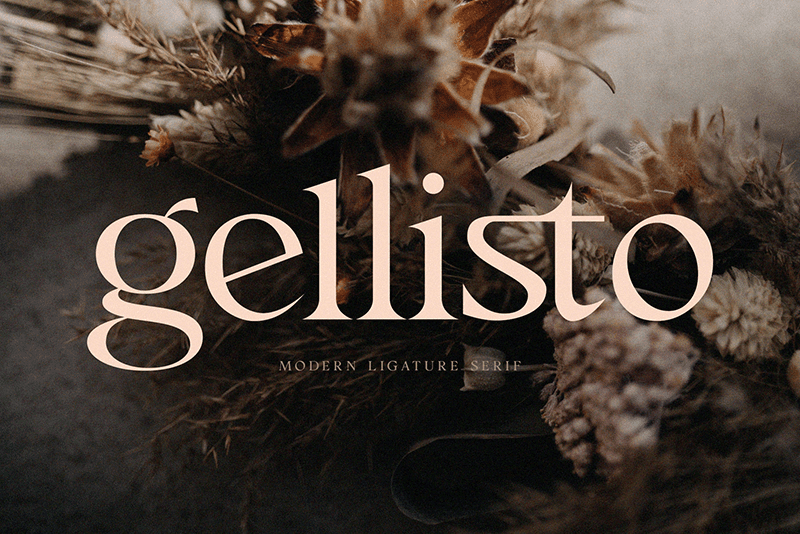
Presentamos Gellisto Modern Ligature Serif. Gellisto es una tipografía serif moderna, elegante y sofisticada, ideal para usar como display para encabezados, logotipos, branding, revistas, empaques de productos e invitaciones. Gellisto tiene líneas limpias y curvas suaves que le dan a cualquier proyecto un toque extra de clase.
#2 Nexa
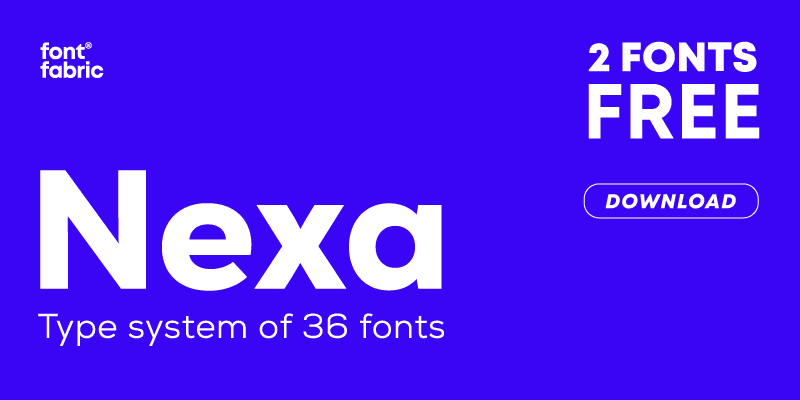
La familia de fuentes Nexa es adecuada para encabezados de todos los tamaños y bloques de texto tanto en el ancho y el alto máximo como mínimo. Los estilos de fuente Nexa son aplicables para cualquier tipo de diseño gráfico digital, web, impreso, superficies duras, telas junto con carteles, logotipos y branding.
#3 Billion Dreams
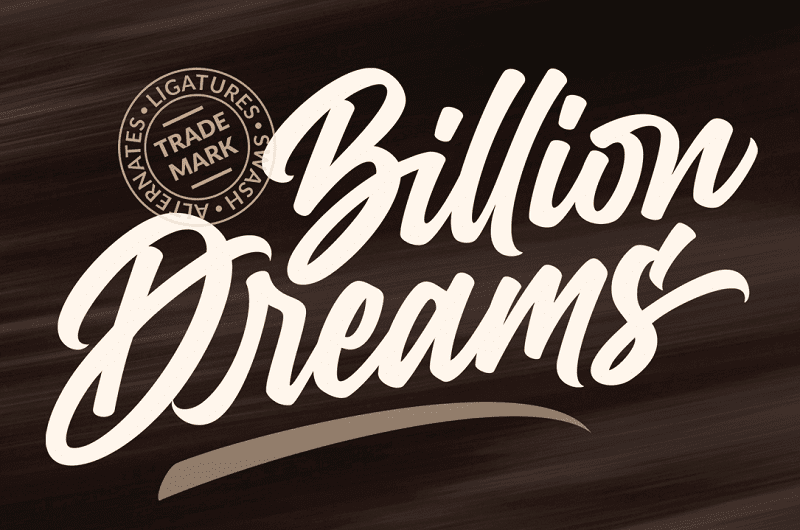
Se trata de una grandiosa fuente script que simula un trazo a mano. Perfecta para refrescar un diseño y hacerlo amigable.
#4 Lostar
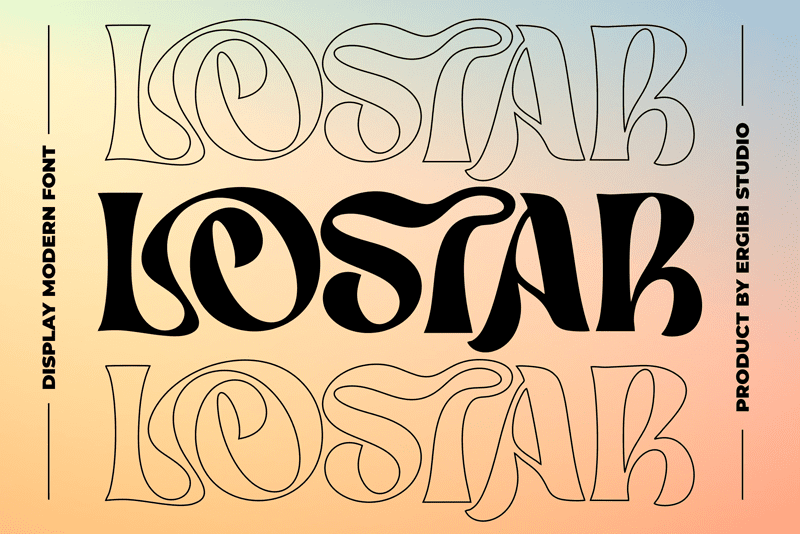
Fuente Moderna de Pantalla. Esta fuente tiene una forma de letra única y audaz, que la hace ideal para ser utilizada en temas de diseño modernos y minimalistas. Las ligaduras únicas en la serif hacen que este tipo de letra sea fresco y se destaque más que la fuente serif regular, perfectamente para titulares, logotipos, carteles, empaques, camisetas, cafeterías, restaurantes, encabezados de revistas, letreros o tarjetas de regalo/postales, cafés y bodas o cualquier tipo de propósito publicitario.
#5 Big Noodle Titling
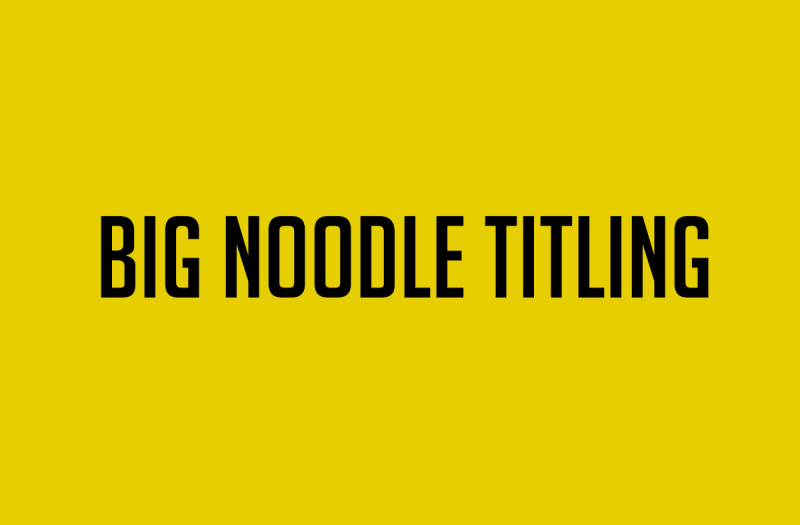
Esta es una fuente sans serif moderna con 3 fuentes! Presentamos Big Noodle Titling. Un conjunto genérico de mayúsculas construido sobre el principio de ancho uniforme gótico, construido a partir de formas cuadradas y un acabado simplificado, Big Noodle Titling ofrece una excelente claridad en cualquier medio. Las características clave de Big Noodle son su utilidad y su aspecto poco notable.
#6 Bebas
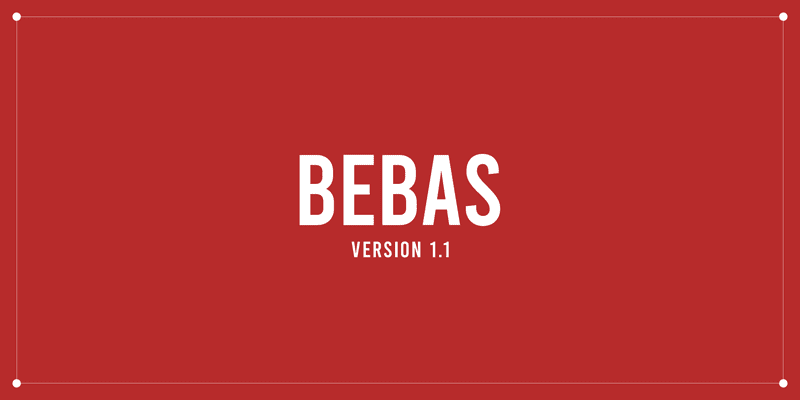
Bebas es una fuente de visualización gratuita para titulares, subtítulos y títulos diseñada por Ryoichi Tsunekawa.
#7 Camera Obscura
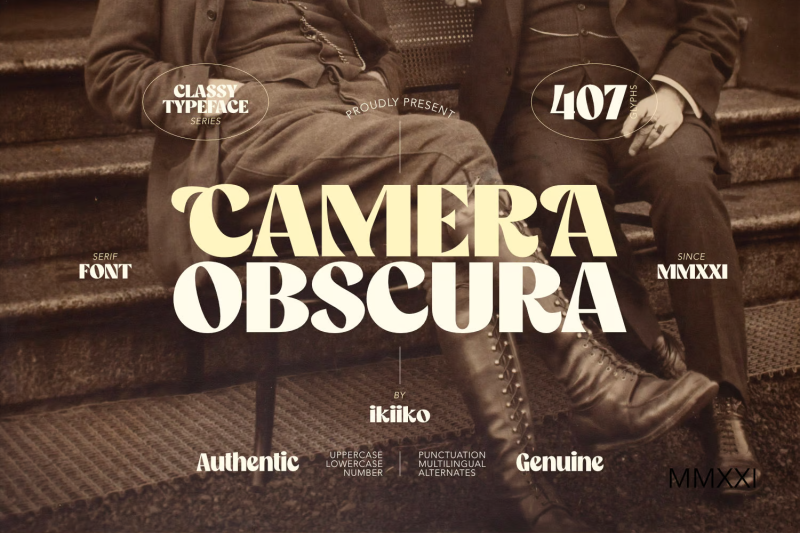
Camera Obscura se inspiró en la tipografía de un periódico antiguo de Nueva York. En particular, este tipo de letra está diseñado para dar un aspecto formal pero de estilo antiguo. Camera Obscura tiene un tipo de letra con serifa y un contraste de negrita a claro. Un estilo muy utilizado en revistas y medios de comunicación de su época. Este tipo de letra es perfecto para un diseño formal, un periódico, una portada de revista y también es bueno para productos vintage, alimentos y bebidas, citas o simplemente como un texto elegante sobre cualquier imagen de fondo.
#8 Cralika
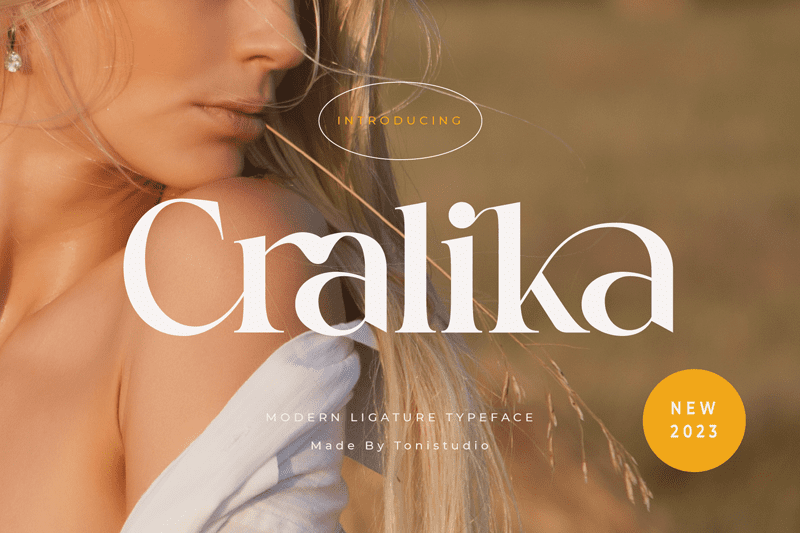
Presentando nuestra nueva fuente que llamamos Cralika, que es una fuente de familia serif que consta de dos tipos, regular e itálica. Cralika es una fuente muy moderna y sofisticada con curvas únicas y un flujo elegante, Cralika puede dar una sensación moderna a tus proyectos. Cralika es perfecta para proyectos de branding, logotipos, diseños de bodas, publicaciones en redes sociales, anuncios, empaques de productos, diseños de productos, etiquetas, fotografía, marcas de agua, invitaciones, papelería y cualquier proyecto.
#9 Mont
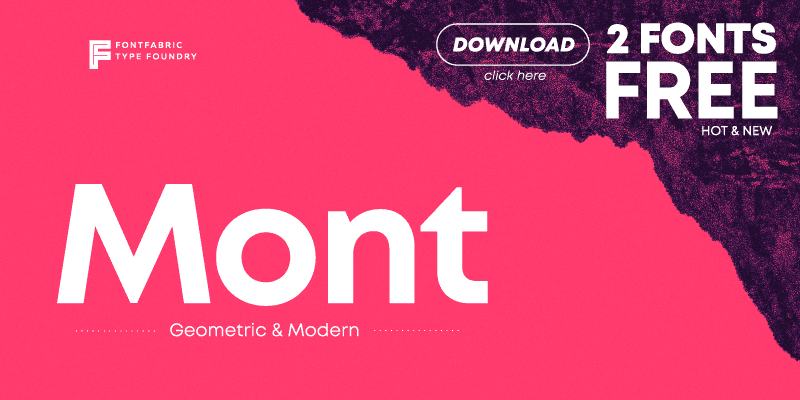
La familia de fuentes Mont es una tipografía sans-serif geométrica de Fontfabric que consta de 10 pesos que van desde Hairline a Black con cursivas a juego.
La característica equilibrada de la familia de fuentes Mont con detalles únicos, como la “t” puntiaguda y la altura de la x prominente, la hace perfecta para titulares fuertes y logotipos sobresalientes, pero también adecuada para textos largos.
#10 Gobold
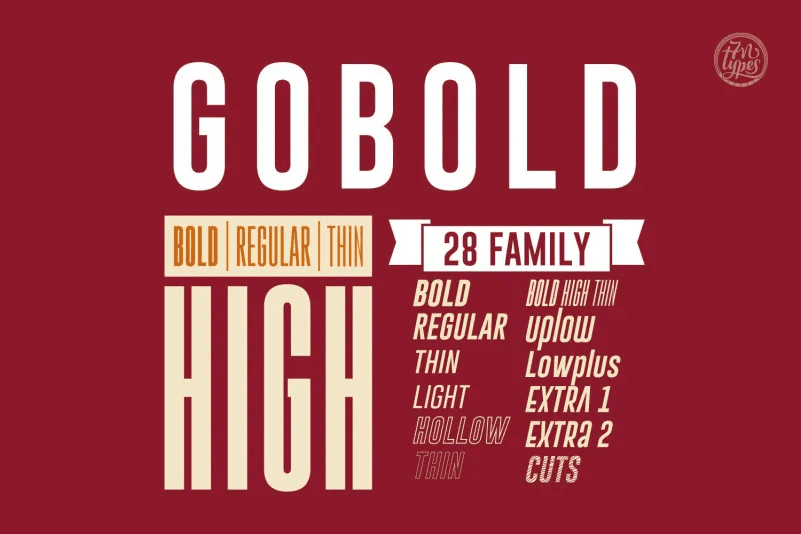
Gobold Sans Serif Font es una fuente sans serif vintage, creada para ser utilizada en logotipos, impresión, branding, señalización y cualquier otro tipo de proyecto al que quieras añadir un toque clásico. Gobold es una impresionante y versátil familia de fuentes sans serif con 28 variaciones. Cada variación se adapta al resto de la familia, lo que hace que Gobold sea útil para cualquier proyecto.